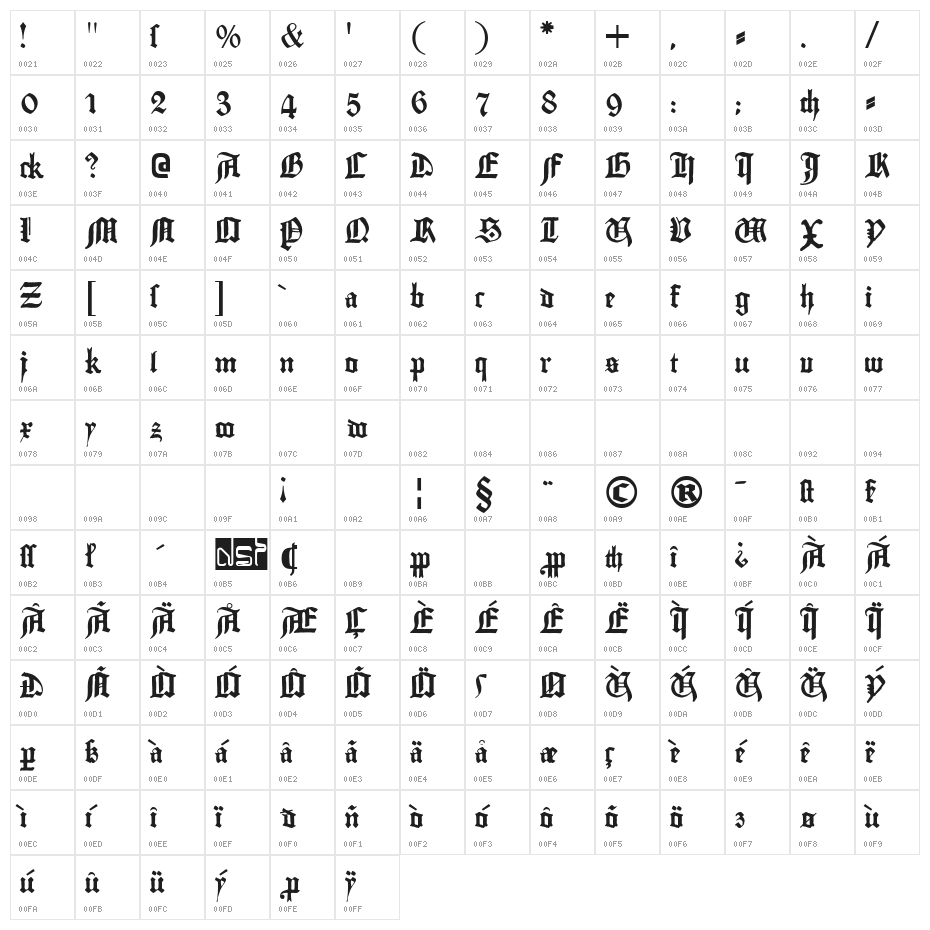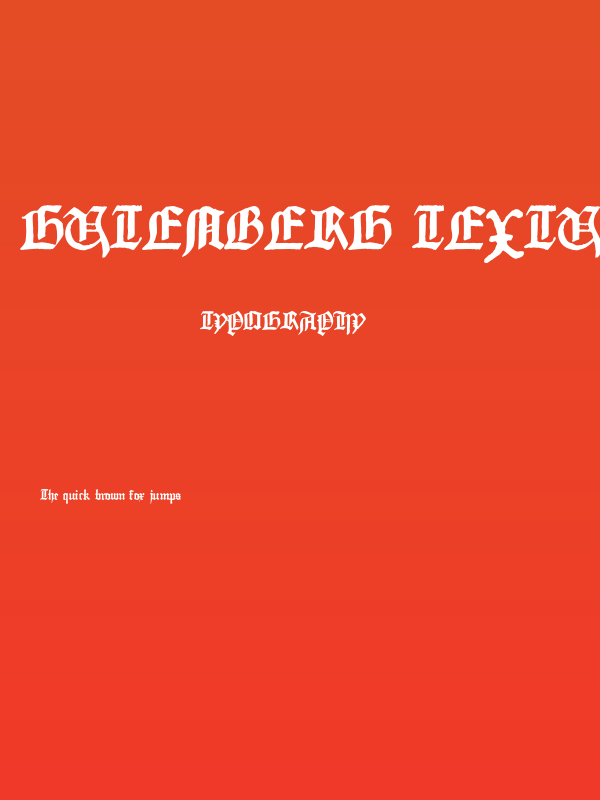
Gutenberg Textura Font
| Gesamtstil | Vintage |
| Vorgeschlagene Projekte | Ideal for historical documents, certificates, book covers, or any project requiring a medieval or gothic aesthetic. |